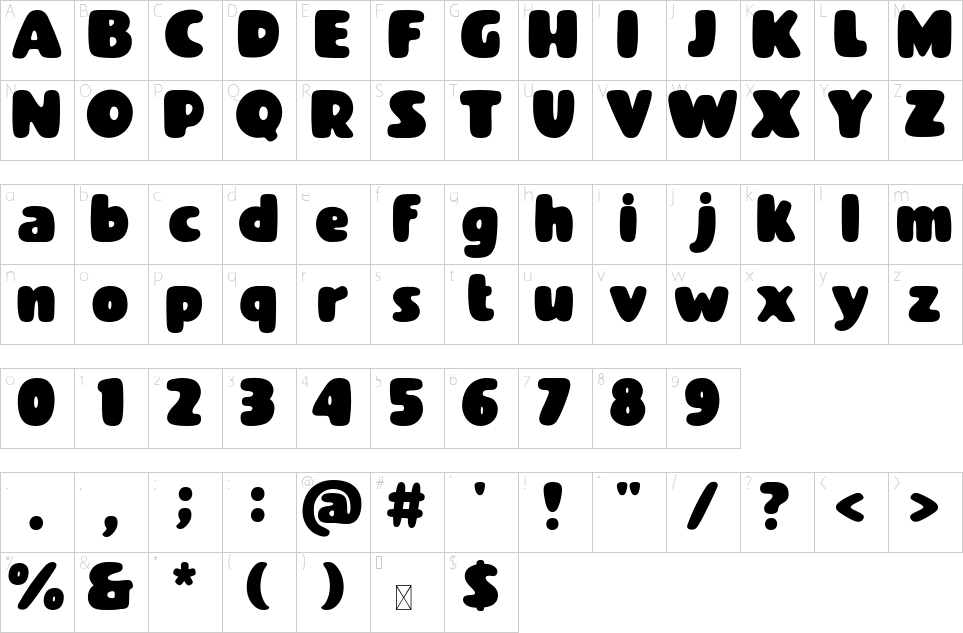
Descubra a magia dos bumbos sonhadores com a fonte Dreamy Bubble! Esse recurso gráfico original foi projetado pela incrível equipe do jimtype studio, e já foram baixados mais de 1.048 vezes este encantador conjunto de letras. Com suas formas ondulantes e cores pastel, essa fonte é perfeita para tornar seus designs únicos e alegres. Seja para adicionar um toque romântico em um design de anúncio ou criar uma experiência visual relaxante em sua próxima página web, as bolas sonhadoras podem ser o elemento perfeito para levar seu trabalho ao próximo nível. Não deixe de experimentar essa fonte encantadora disponível gratuitamente e veja como ela pode transformar seus projetos.